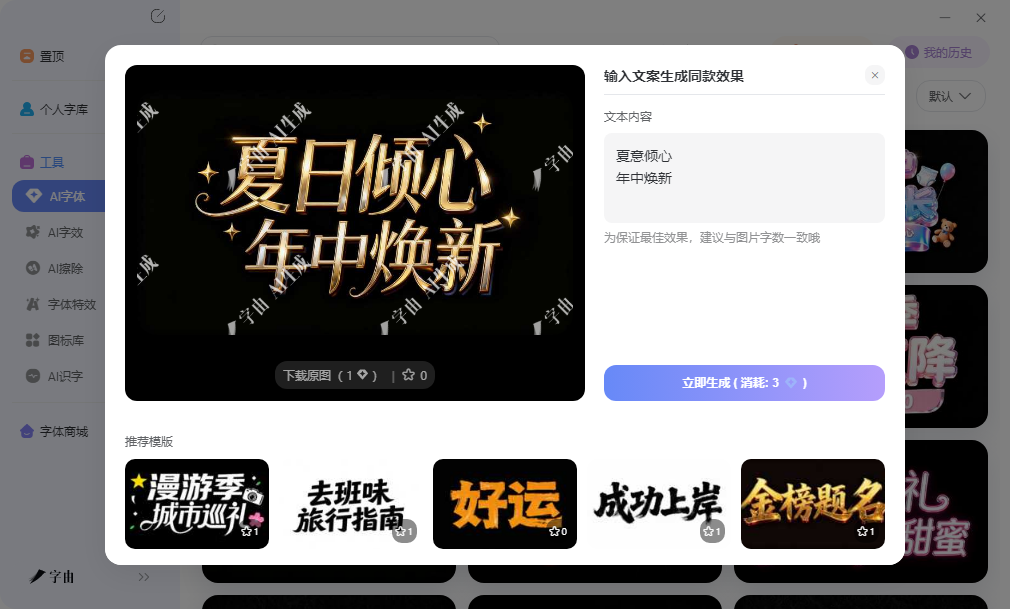
字体在线转换神器,输入文字秒变花式样式
很多人做社交媒体内容或者设计海报时,想给文字加点花样,但又不想打开复杂的设计软件调参数。在线转字体的需求其实很常见,核心就是输入普通文字,快速获得花式效果,然后直接复制使用。这篇文章整理了五个工具,覆盖 AI 生成、装饰字符、移动端输入和社交美化等场景。
字由目前对于需要在线转字体并直接用于设计项目的场景,字由的 AI 字效功能是一个比较直接的方案。AI 字效内置了多种特效模板,覆盖立体、金属、霓虹、投影等风格。操作流程是选模板、输文字、生成、下载图片。生成的结果是 PNG 格式,背景透明,可以直接叠加到其他素材上使用。做海报标题、公众号封面、电商详情页主文案都很方便。对于系列物料,固定选一个模板批量生成,风格统一,比在传统软件里反复调图层快很多。
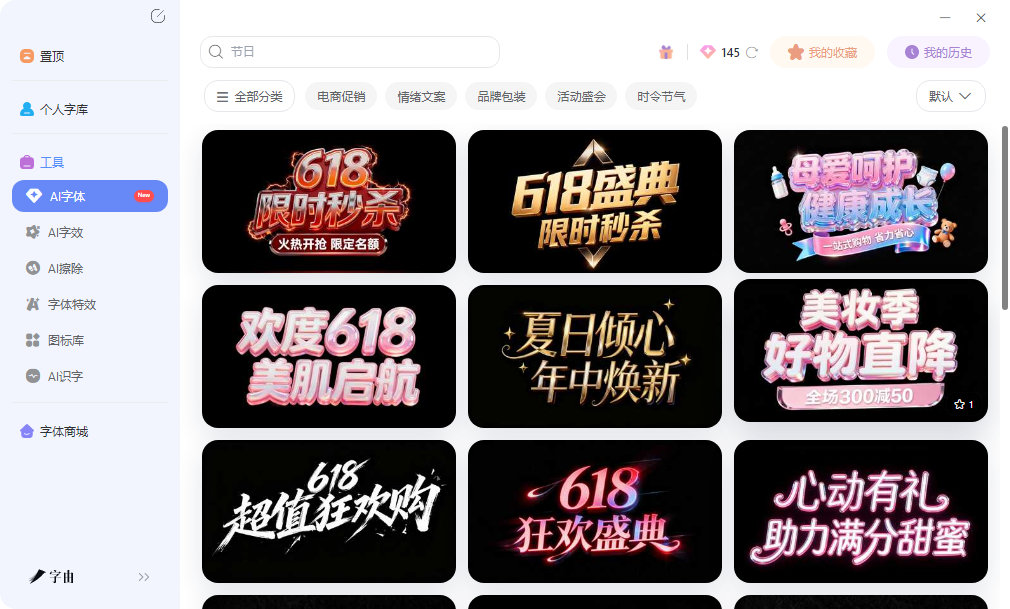
AI 配字则解决选字困难。输入关键词比如科技感、复古风,系统推荐匹配的字体组合,相当于一个快捷预览入口。推荐结果里包含大量免费商用字体,看到合适的直接激活,就能在 Photoshop、Illustrator 里调用。两个功能都支持网页版,临时在别的电脑上打开浏览器就能用,收藏记录和生成的素材会自动同步到个人云字库。
Musely 是一款免费 AI 字体生成器,支持输入文字后通过 AI 生成自定义文本效果。界面提供了进阶设置选项,可以调整字体风格和生成数量,语言选择里包含中文。对于想要在线转字体并获得独特效果的用户来说,AI 生成的方式比套用固定模板更有探索空间。
操作流程是输入文字内容,选择语言,调整进阶参数,点击生成。系统会返回带特效的文字图片,可以直接下载使用。Musely 的 AI 生成结果风格比较多样,每次生成可能有差异,适合需要创意方案的场景。不过生成速度受网络影响,高峰期可能需要等待。生成的图片分辨率足够在社交媒体和网页展示中使用,但如果是印刷级别的大尺寸输出,可能需要确认清晰度是否达标。
Webflow Font Generator 是一个在线转字体工具,主打装饰性 Unicode 字符的快速预览和复制。首页把字体按 All、Cool、Fancy、Cursive、Small、Glitch、Zalgo、Symbolic、Gothic 等类型做了分类,输入文字后页面会实时展示各种样式效果。使用方式很简单,在输入框里打字,下方会批量显示不同风格的转换结果,每个结果旁边都有复制按钮,可以直接粘贴到社交媒体、聊天软件或者文档里。这种即时复制的设计很适合需要快速发一条带特效文字的动态,或者给昵称、标题加点装饰感。
需要注意的是,Webflow Font Generator 生成的结果是 Unicode 特殊字符,不是真正的字体文件。在微信、微博、Discord 等平台可以直接显示,但在 Photoshop 或者 Word 里无法作为字体来调用和编辑。它的优势是零门槛、零安装,打开网页就能用,局限性在于适用平台有限,且不支持二次设计调整。
Fontfy 是一个移动端在线转字体方案,主要形态是手机键盘应用。它提供了 80 多种独特字体样式,覆盖 bold、fancy、cursive、symbolic 等风格。安装后可以在 Instagram、TikTok、WhatsApp 等社交平台直接输入花式文字,不需要复制粘贴,打字的同时就能看到特效。这个工具的定位很明确,就是解决移动端输入花式文字的需求。传统方式下,你要先在网页端生成特效文字,复制,再切换到社交软件粘贴。Fontfy 把这个流程简化了,直接在键盘里选样式,打字就是特效字。对于经常用手机发社交媒体内容的人来说,这种方式效率更高,体验也更流畅。
ArtFonts 是一个专注社交媒体美化的在线转字体工具,输入文字后可以生成多种艺术风格的效果,广泛适用于 Instagram、TikTok、Facebook、Twitter 等平台。界面很简洁,顶部一个大输入框,输入文字后下方会展示各种美化结果。
ArtFonts 的风格偏向 aesthetic 美学字体,生成的效果比较精致,适合做社交媒体个人简介、帖子标题或者评论装饰。和前面几个工具一样,它输出的也是 Unicode 特殊字符,不是可安装的字体文件。使用场景集中在需要文字装饰但不需要后期编辑的场合,比如发一条带特效的社交动态,或者给账号昵称换个风格。
最后提醒一点,无论是用字由还是其他工具,输出前最好确认一下最终效果在目标平台上的显示情况。Unicode 特殊字符在不同设备、不同软件里的兼容性有差异,有些平台可能不支持某些符号,显示出来会变成方框或者乱码。AI 生成的图片也要注意分辨率,印刷用途的话建议提前测试清晰度。先把这些细节确认好,再批量生成,能省去不少返工时间。